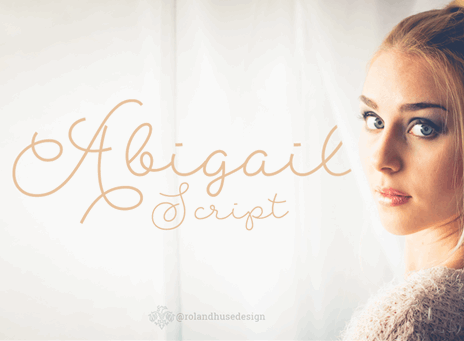
A fonte ‘Abigail Script Font’ é uma mão-dura elegante que combina elementos delicados com linhas fortes e curvas suaves. Ela foi criada pelo designer Runes&Fonts e oferece um visual único, ideal para design gráfico pessoal ou de pequeno negócio. Completamente personalizável, a fonte inclui espaçadores estilizados, ligaturas padrão e até mesmo as “swashes”, que são linhas curvas adicionadas ao final das letras. Para o uso comercial e na versão completa do produto, os usuários devem visitar o site da Roland Huse ou enviar um e-mail para . A versão gratuita inclui todas as letras minúsculas e maiúsculas, números e espaçadores, enquanto a versão completa contém pontuação, alternativas estilizadas, ligaturas estilizadas, além de “swashes” e outros detalhes refinados. A fonte tem um design muito criativo que vai desde o uso em nomes de marca até elementos gráficos de cartões de presente. Ela também combina bem com designs para sites pessoais, cartas de amor, editoriais, logotipos e artigos de blog. Como designer ou profissional que valoriza a qualidade e diversidade das suas criações, você vai se apaixonar por essa fonte única e elegante. Sempre mantenha crédito ao autor e não modifique em nenhuma circunstância o design da fonte.